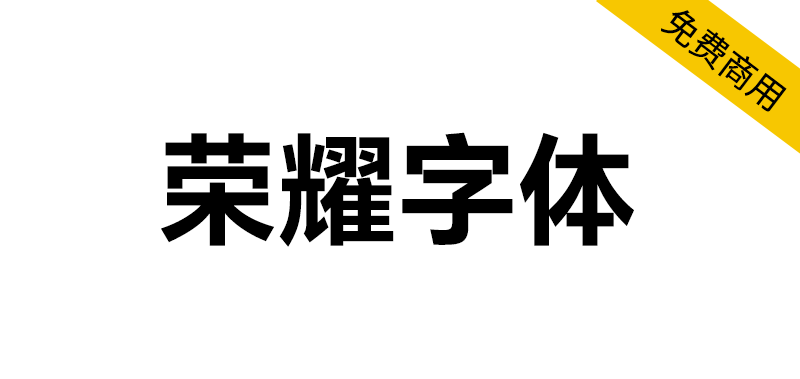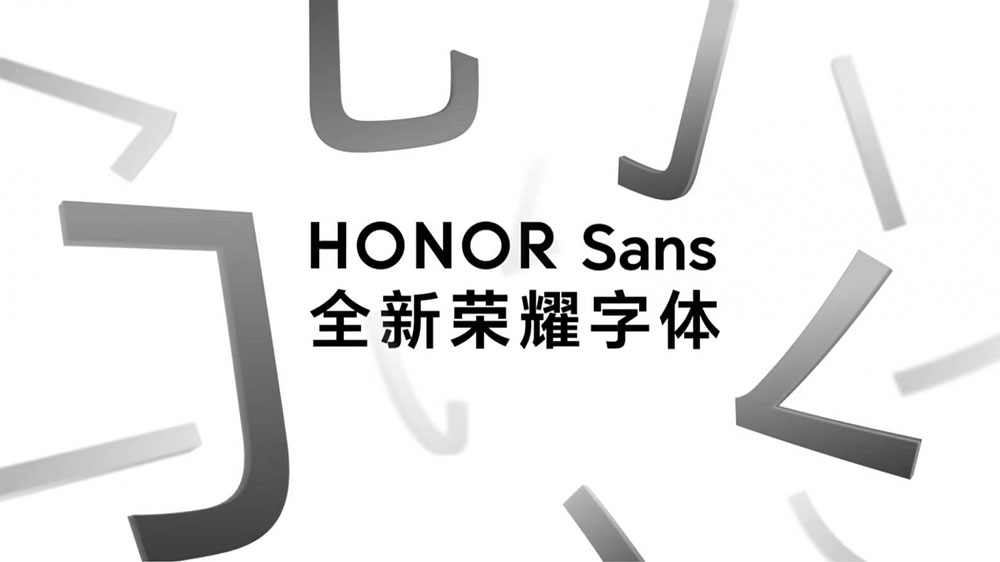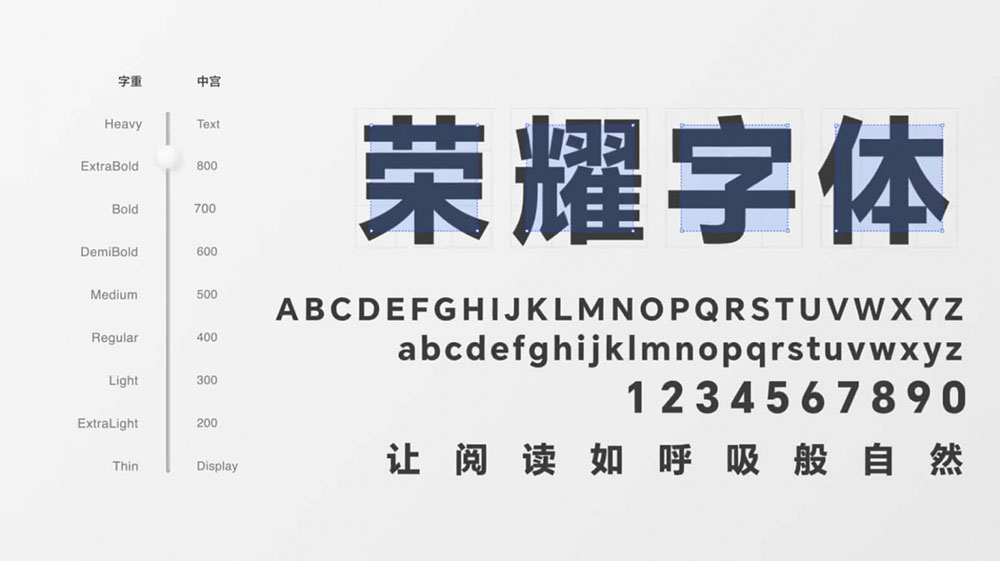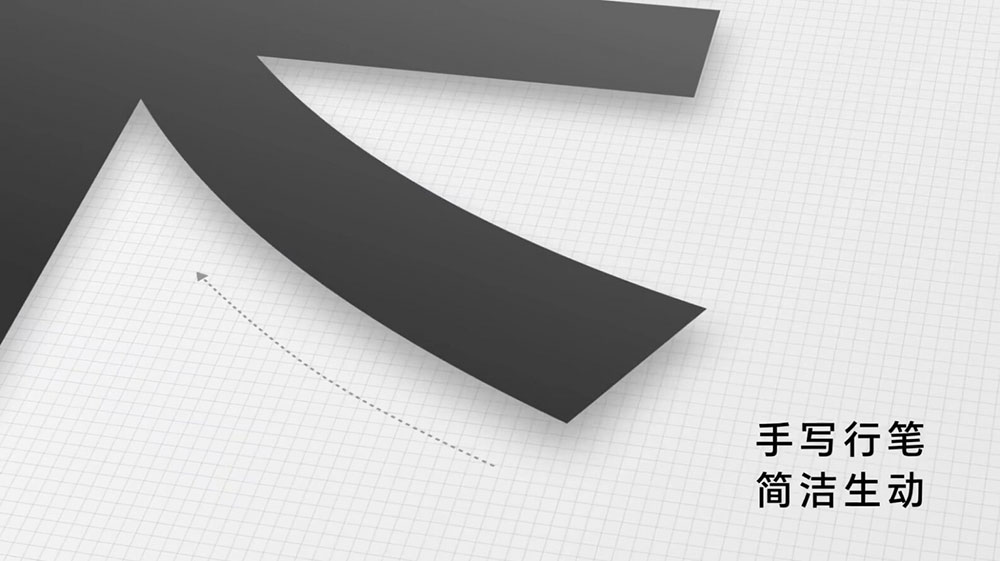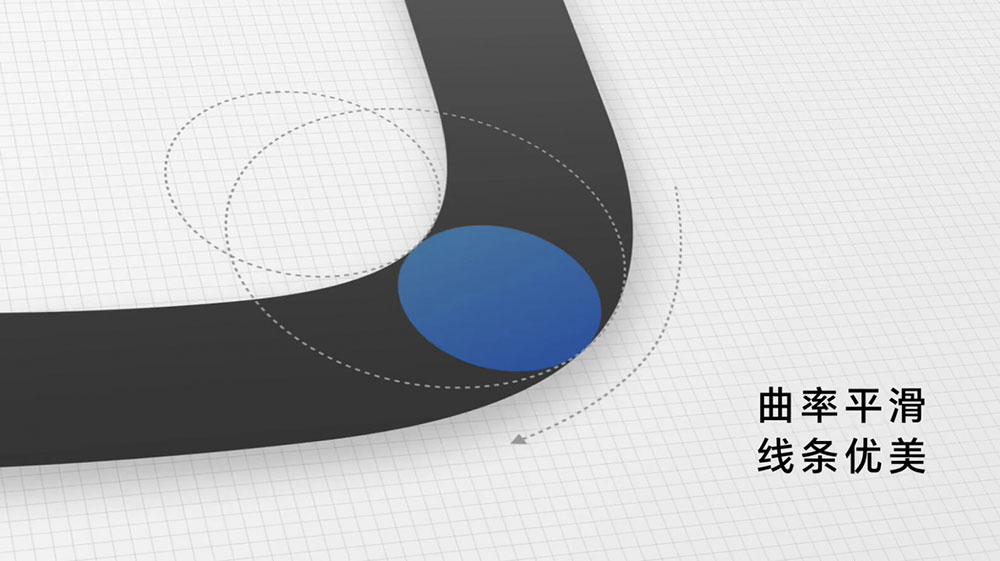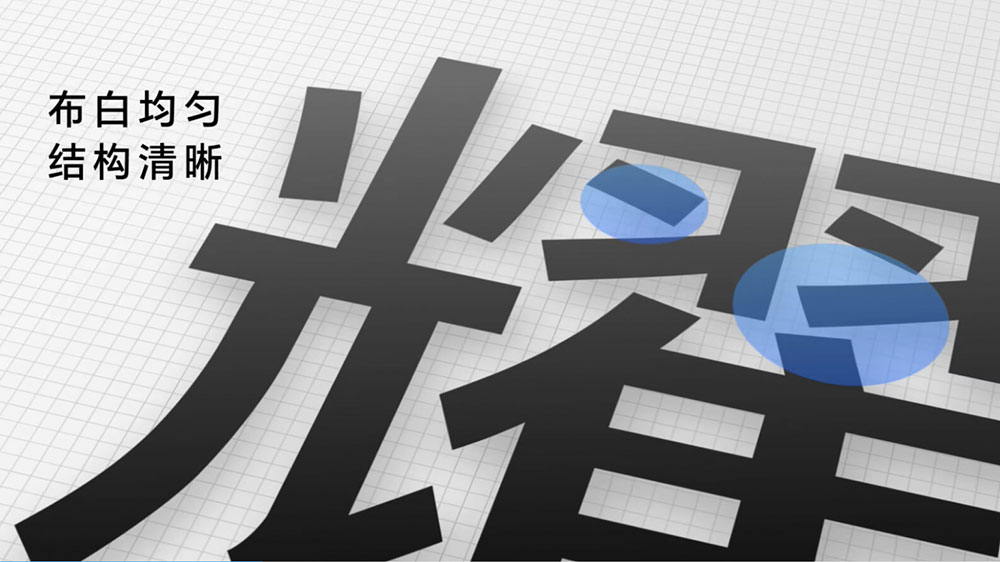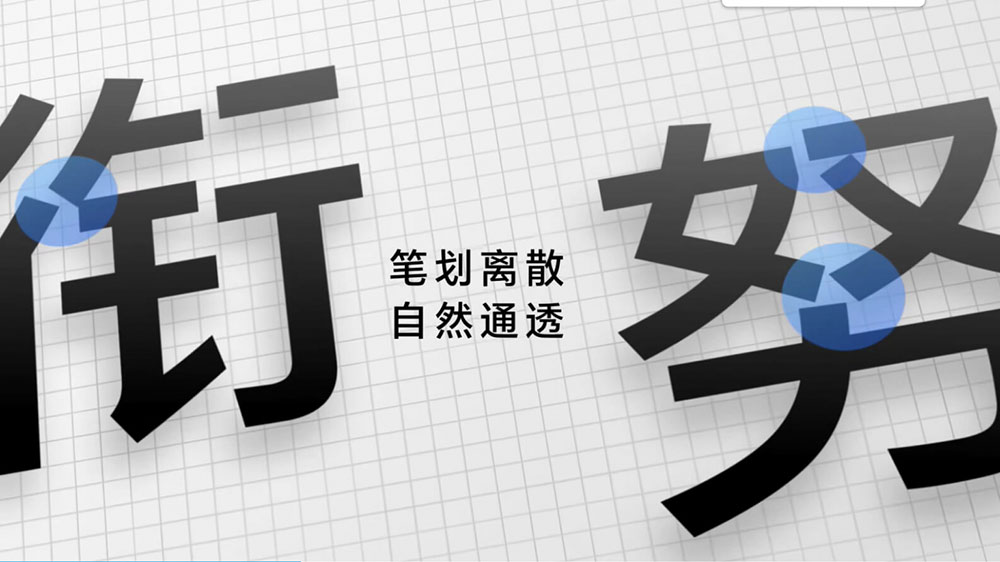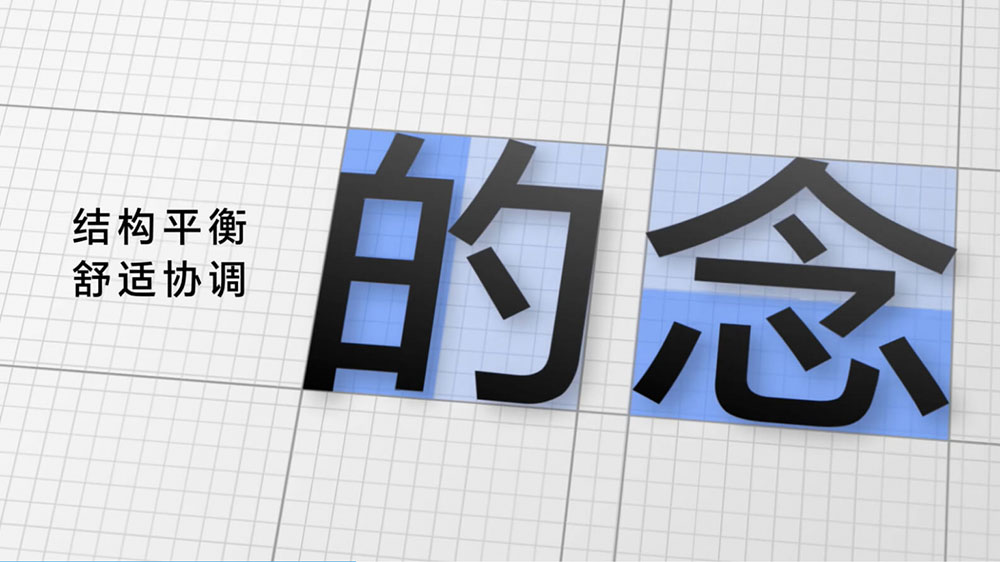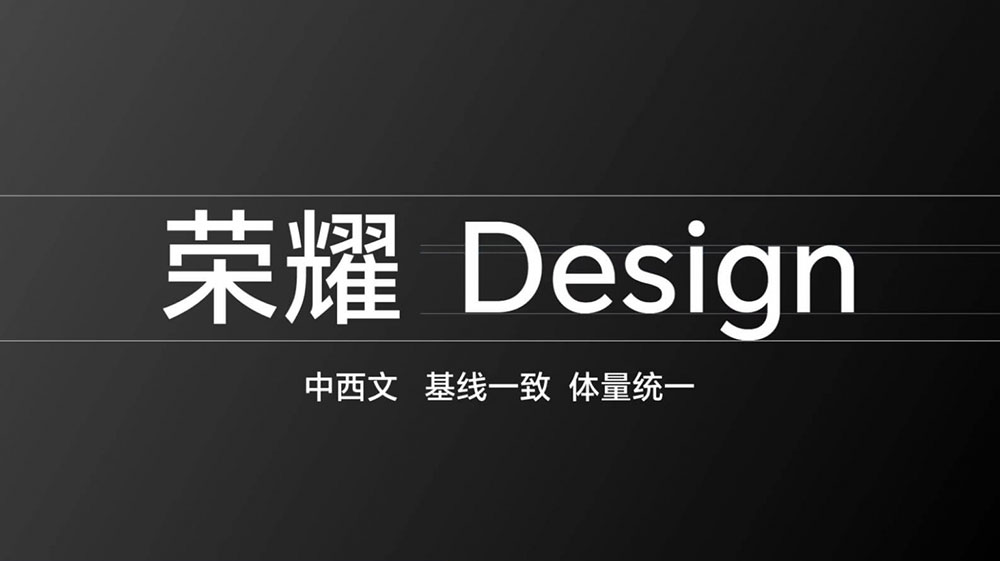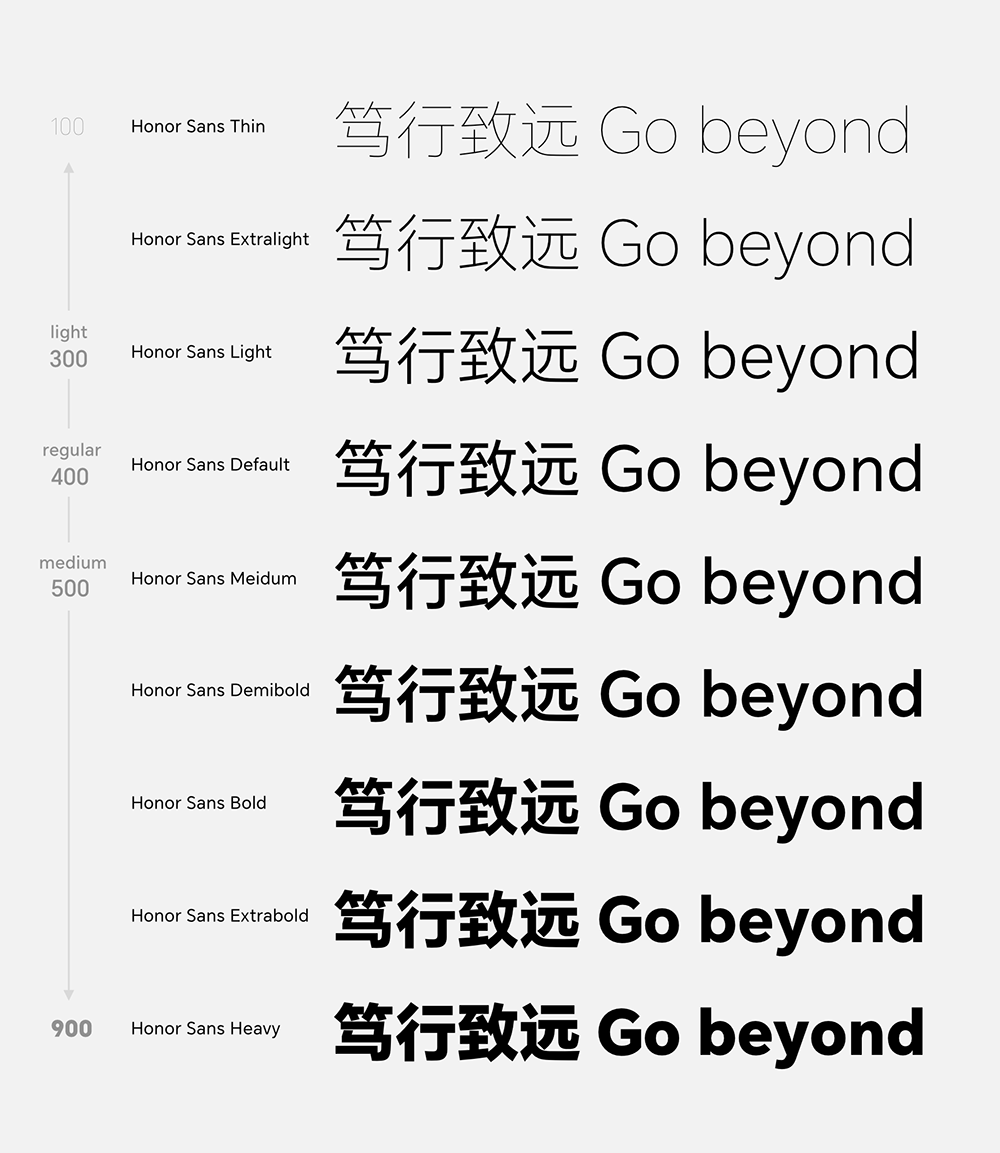
在荣耀 MagicOS 7.0 发布会上,荣耀还带来了全新的荣耀字体(HONOR Sans) 字体,号称是业界首款支持字重和中宫双重无极可变的字体,将荣耀字体与 UI 融合,通过间距优化,让排版更整齐,层次更清晰。
HONOR Sans 以黑体为基础,能够根据用户需求对字重和中宫进行调节,从而在不同环境下均能确保字体的匀称美观。在设计上,HONOR Sans 相比标准的黑体则在笔画曲率、结构布局上进行了优化,在不影响字体可读性的前提下,有效提升了字体的舒适性,降低了长时间阅读时对视觉造成的疲劳。为创作者带来了一种新的黑体选择,在海报、视频字幕、说明文字等方面都能充分起到作用。
字重无级调节功能:Honor sans增加了Thin、Extralight、Light、Default、Medium、Demibold、Bold、Extrabold、Heavy的字重能力,满足不同人群的对字体对比度的需求,满足不同领域字体一致的清晰度,开发者可以选择需要的字重来构建界面的信息层级。
中宫可变功能:中宫作为字体中间区域大小,影响着笔画的疏密。系统可根据字号大小进行适当的中宫调节。字号越小,中宫越大,字形结构越清晰,更易识别;字号越大,中宫越小,字形越挺拔俊秀。